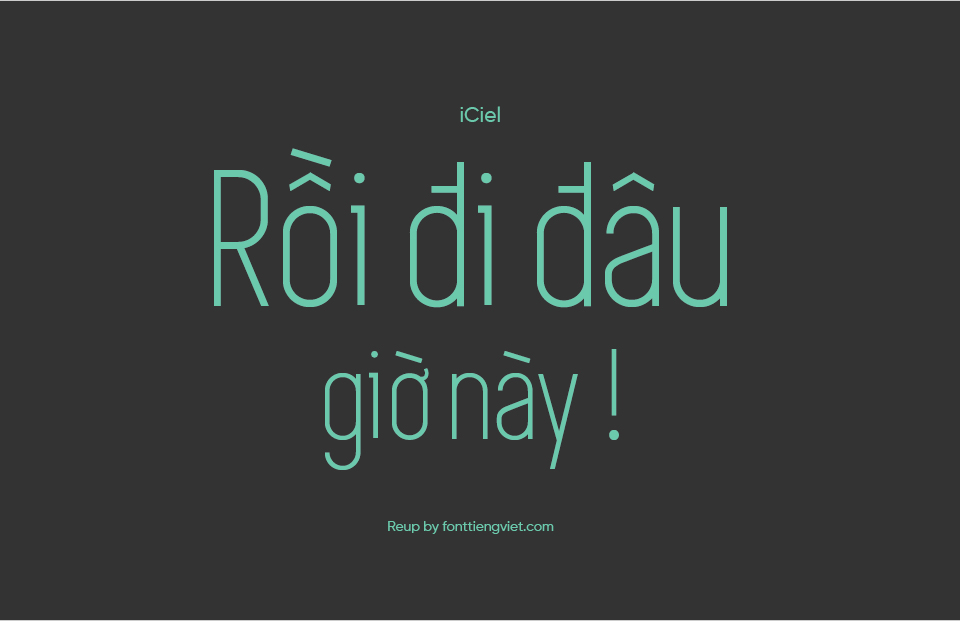
Giới thiệu về Font việt hóa iCiel Simplifica
Trong thế giới đồ họa, việc lựa chọn một Font Chữ phù hợp đóng vai trò quyết định đến tính thẩm mỹ và thông điệp của sản phẩm. Font việt hóa iCiel Simplifica là một sự lựa chọn hoàn hảo cho những ai yêu thích phong cách tối giản và thanh lịch. Đây là một phông chữ thuộc họ Sans Serif với những đường nét thanh mảnh, chiều cao ký tự đồng nhất, mang lại cảm giác dễ chịu cho người xem. Khi được iCiel việt hóa, bộ font này đã trở nên thân thiện hơn với người dùng Việt Nam, giúp các bạn học sinh và giáo viên dễ dàng ứng dụng vào các bài thuyết trình hay dự án học đường mà không lo lỗi dấu tiếng Việt.
Đặc điểm nổi bật của bộ Font việt hóa iCiel Simplifica
Thiết kế tối giản và tinh tế
Đúng như tên gọi của mình, Font việt hóa iCiel Simplifica tập trung vào sự đơn giản tối đa. Các ký tự được thiết kế mảnh mai nhưng vẫn đảm bảo độ rõ nét vượt trội. Điều này giúp không gian thiết kế trở nên thông thoáng, hiện đại và vô cùng chuyên nghiệp. Bộ font này đặc biệt phù hợp cho các tiêu đề lớn, bìa sách hoặc các đoạn văn bản ngắn cần sự tập trung.
Tính ứng dụng cao trong giáo dục
Đối với môi trường nhà trường, việc sử dụng các phông chữ sạch sẽ giúp học sinh tiếp thu thông tin nhanh chóng hơn. Bạn có thể dùng nó để thiết kế báo tường, thiệp mời hoặc các biểu mẫu văn phòng. Sự đồng bộ trong bảng mã giúp quá trình gõ tiếng Việt diễn ra mượt mà trên mọi phần mềm thiết kế phổ biến hiện nay.
Kết luận và cách sử dụng font hiệu quả